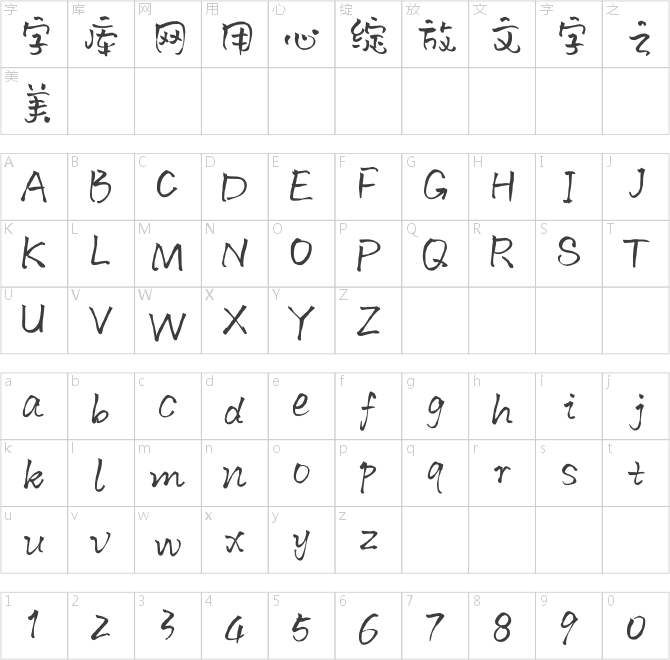
默陌
默陌茶思幽然筆跡是一款水墨風(fēng)格手寫字體,筆觸渾圓溫潤,粗細(xì)對比鮮明,字形豐腴飽滿。點畫俏皮、圓轉(zhuǎn)優(yōu)雅的結(jié)構(gòu)特點豐富了字體的視覺層次,既有傳統(tǒng)書畫的寫意,又兼具現(xiàn)代pop字體的趣味,適用于影視廣告、海報、個性化排版等多種場景應(yīng)用。